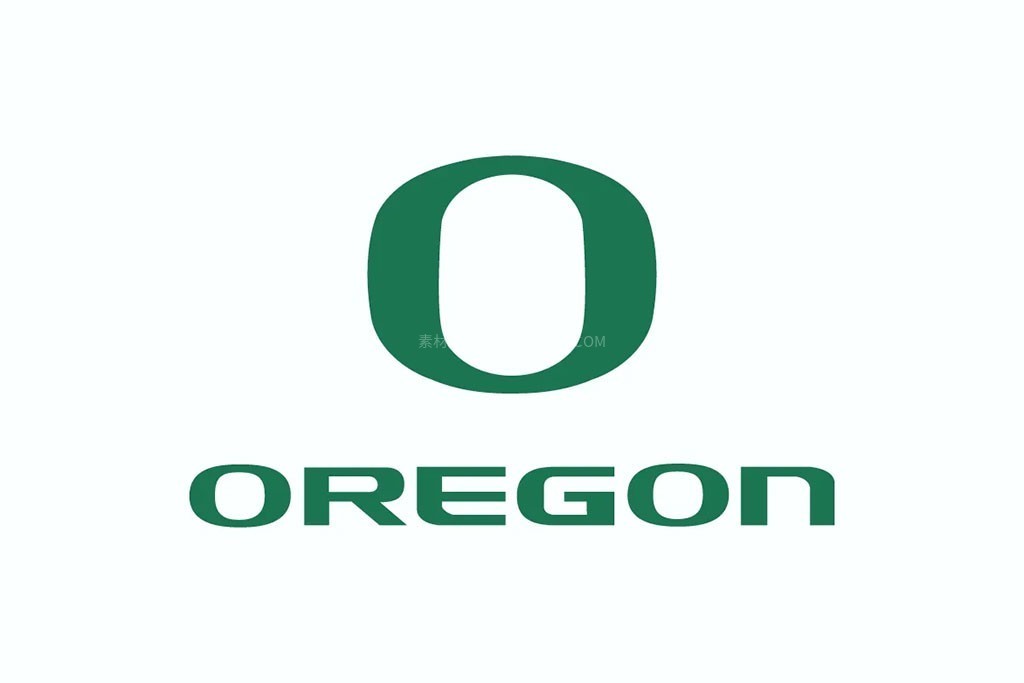
俄勒冈鸭队LOGO队徽字体
这款由耐克公司精心打造的专属字体,专为位于俄勒冈州尤金市的活力四射的俄勒冈大学鸭队量身定制。它标志着始于2018年的品牌重塑计划的巅峰之作,该计划涵盖了全新的队徽、重新设计的队服和充满活力的视觉形象。
俄勒冈鸭队LOGO队徽字体
这种字体不仅仅是一种排版选择;它象征着鸭队的精髓——体现了他们的速度、力量和敏捷。它源自标志性的“O”形符号,象征着大学和俄勒冈州的精神,也概括了球队的身份和精神。